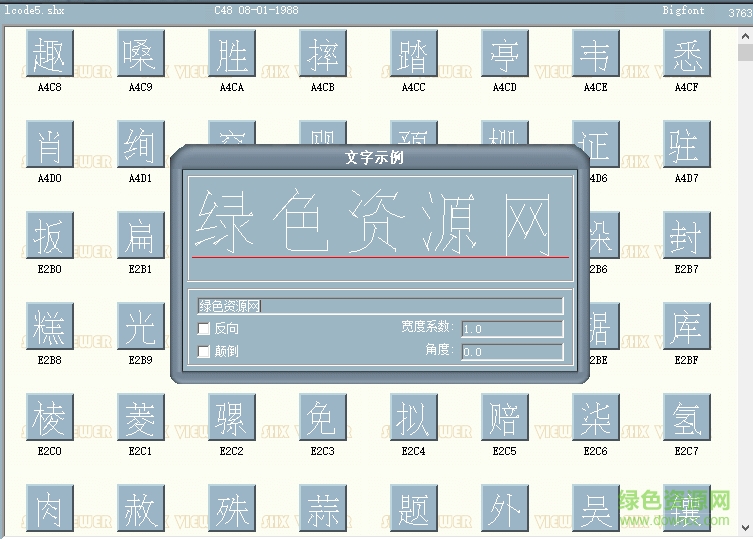
lcode5.shx是一款autocad專用字體。不同的shx文件用途不同,不能隨便替換。需要的用戶下載這款cad文件輔助你的工作學(xué)習(xí)。
SHX字體的優(yōu)點(diǎn):具有較高的編輯、顯示、打印速度。單線條仿宋字字體清秀,適合國標(biāo)制圖。
SHX字體的缺點(diǎn):由于CAD專用字體屬于可自定義字體類型,所以不同公司提供的SHX字體文件名與款式可能各不相同,同樣的文件可能是不同的字體,也可能字體的基本大小比例也不同。從而導(dǎo)致漢字與數(shù)字字母大小不一致,或漢字與數(shù)字字母分開寫時(shí),文字易因替換字體而錯(cuò)位。